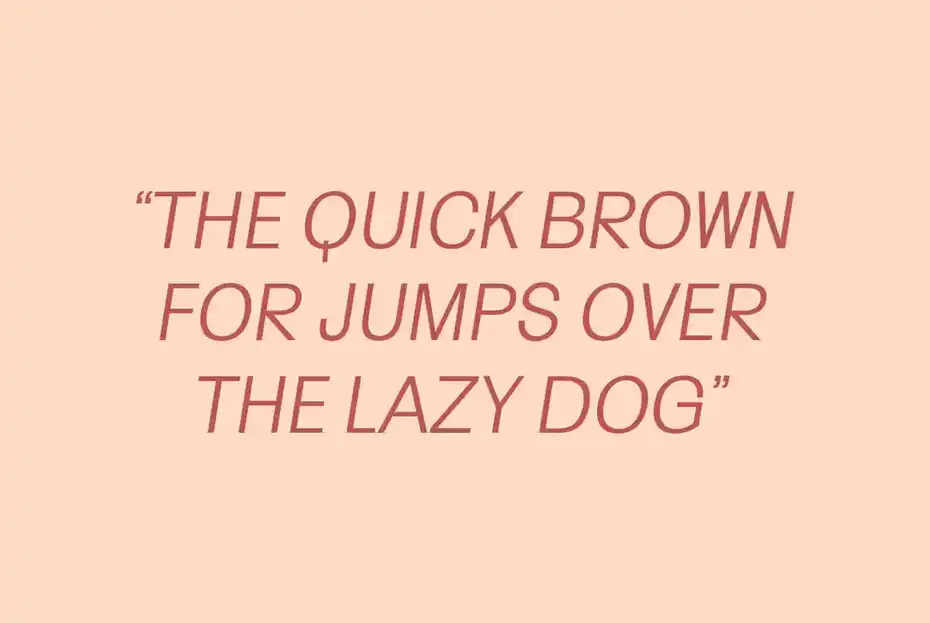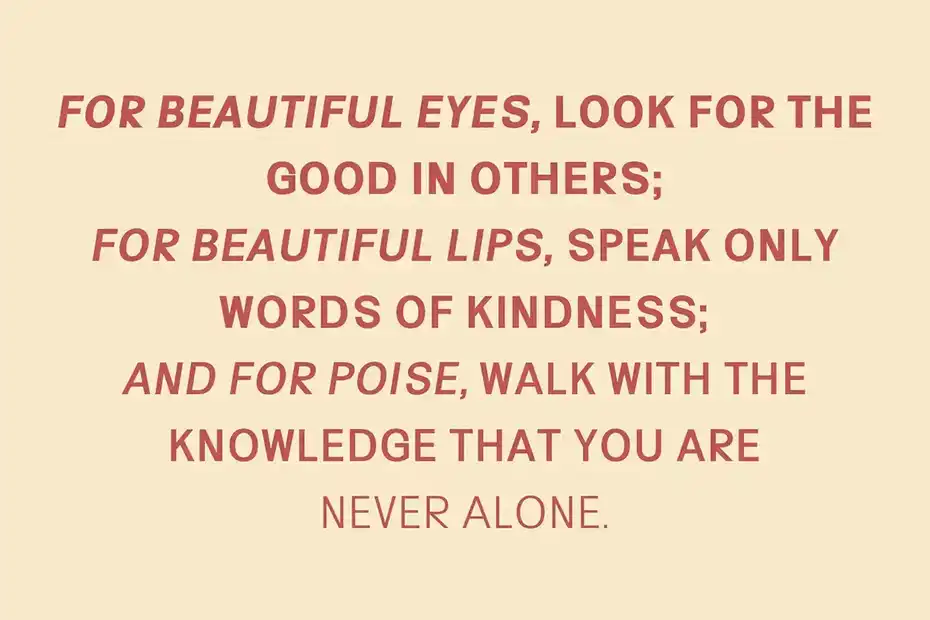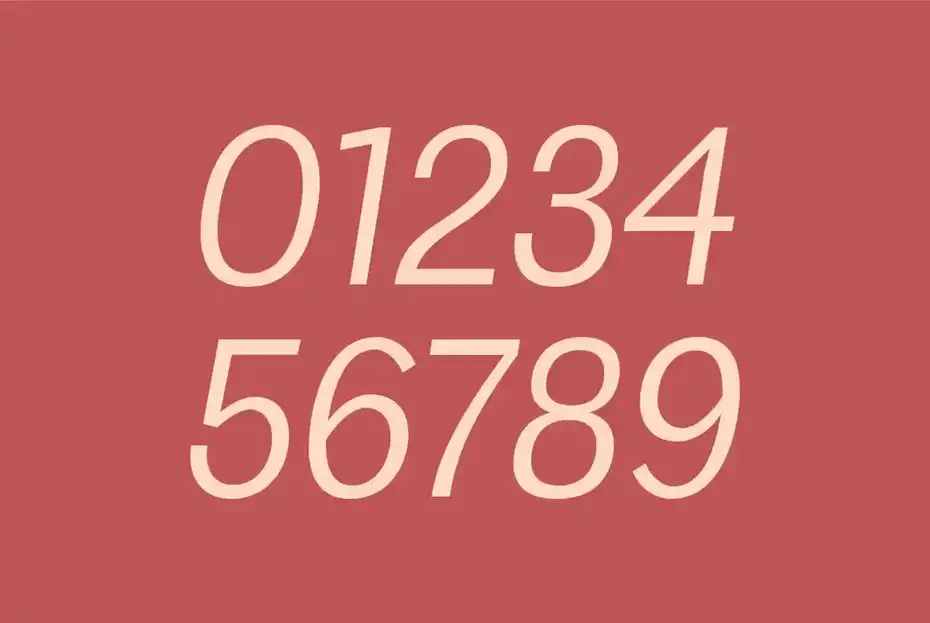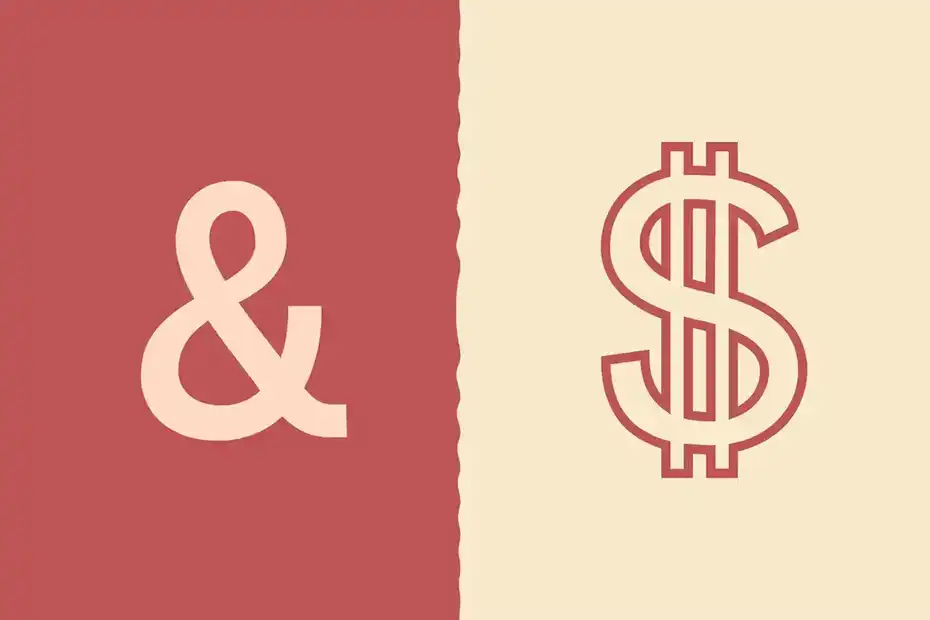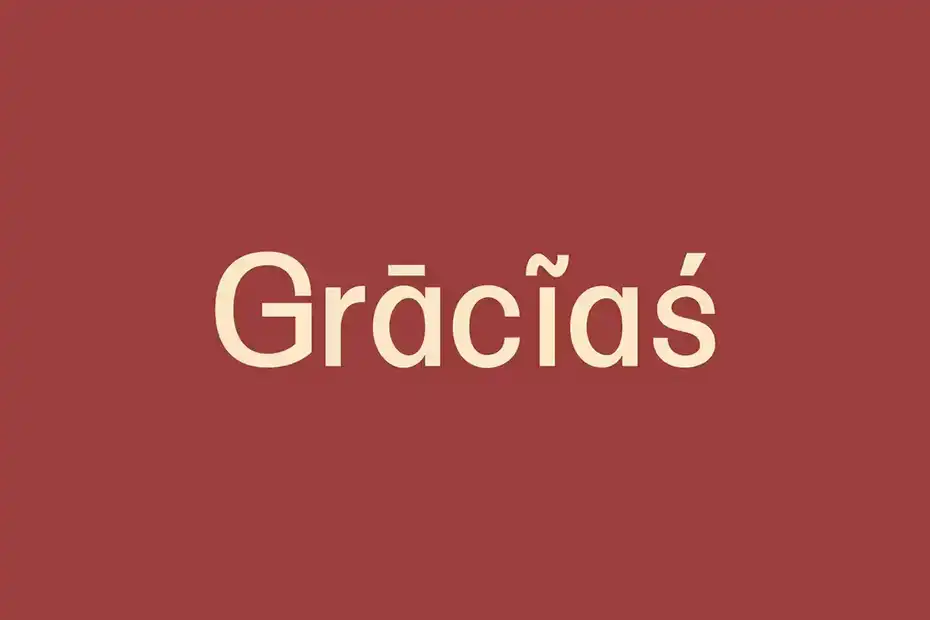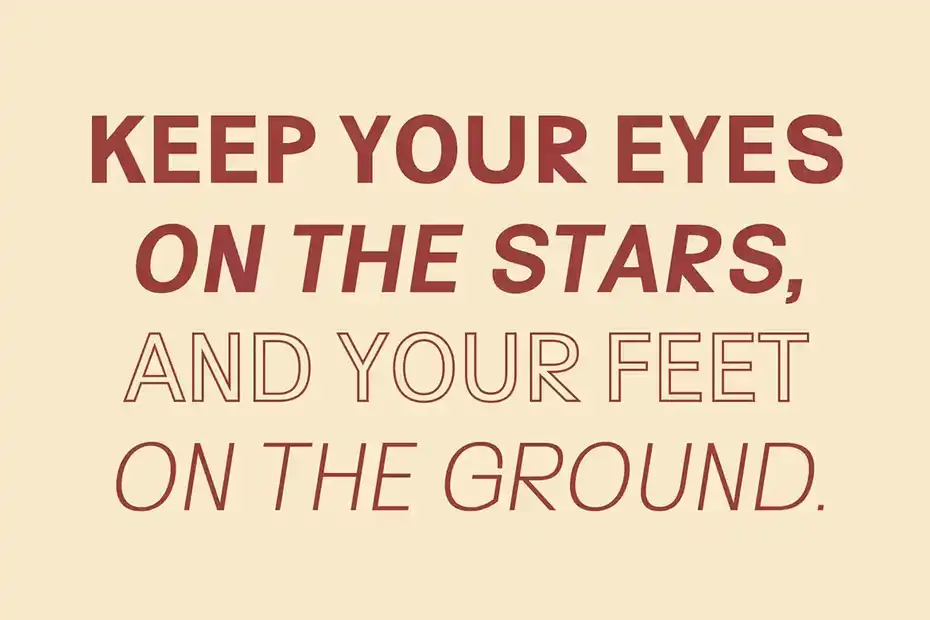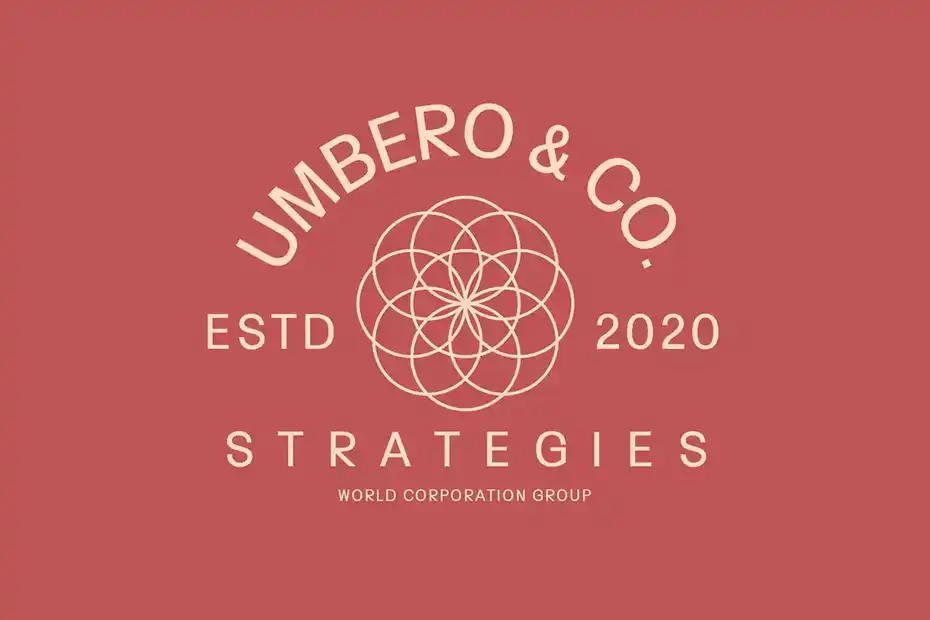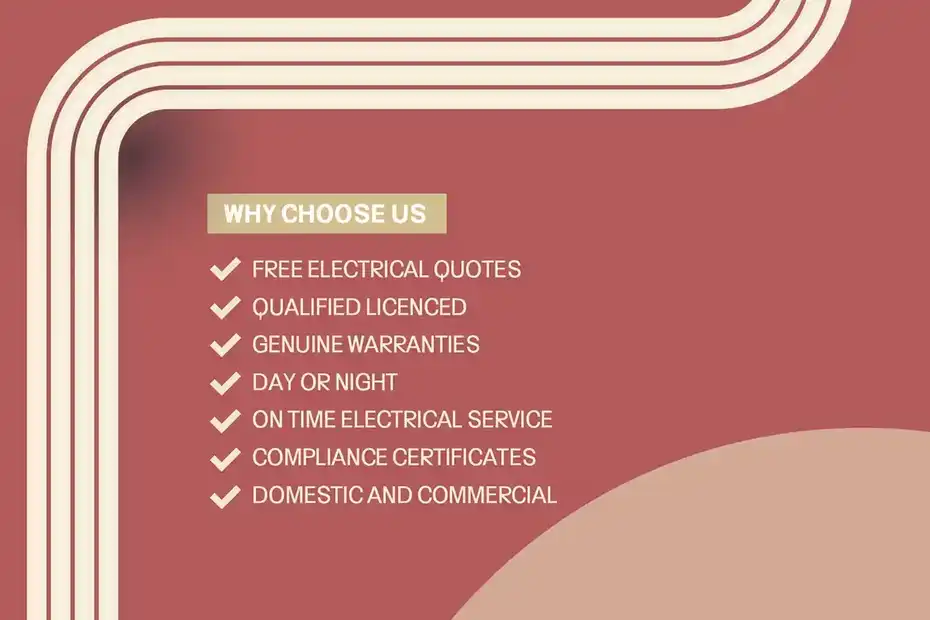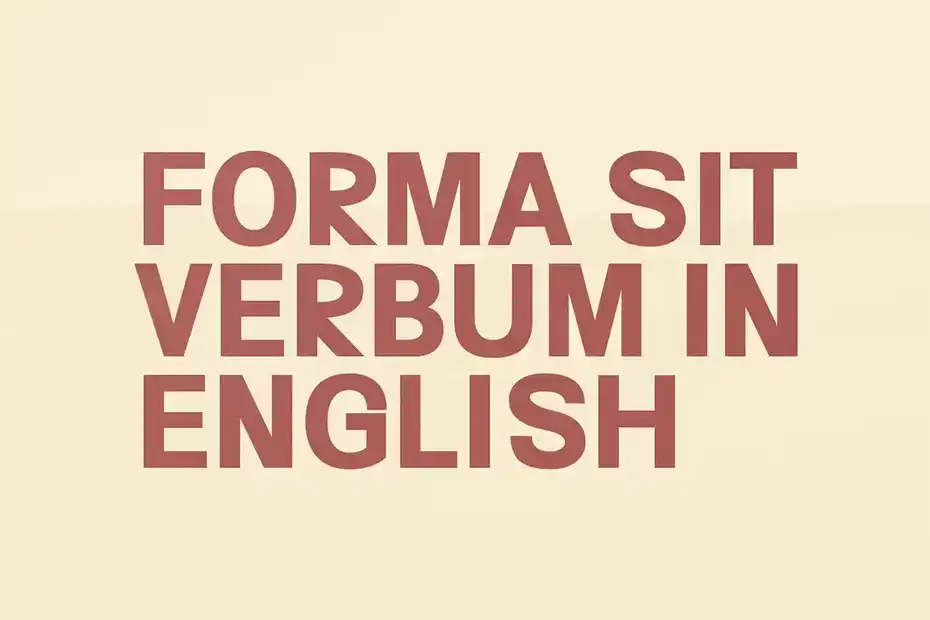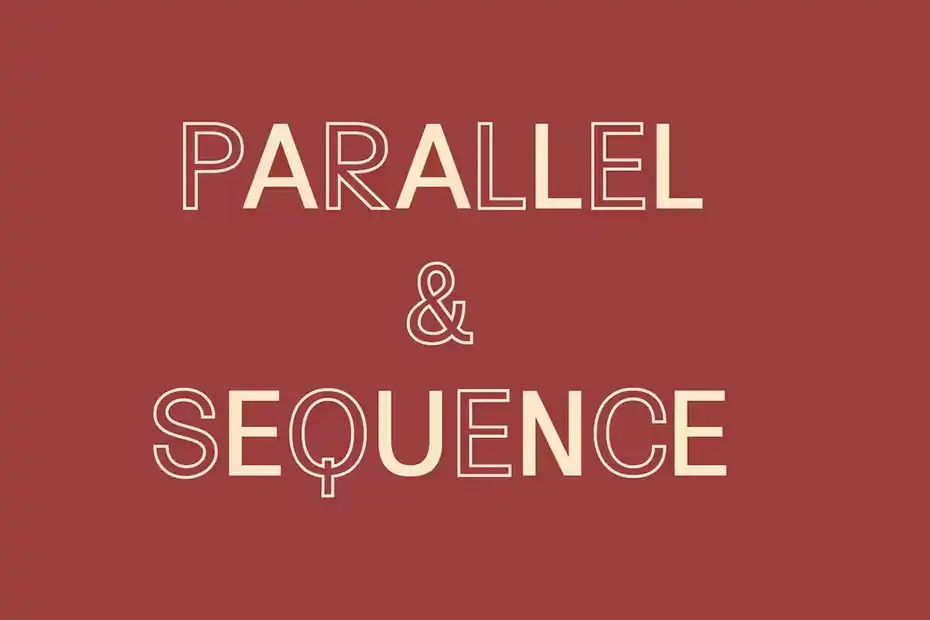
دانلود فونت انگلیسی ساده Hacim Simple Sans Serif Font Family
فونت انگلیسی ساده Hacim Simple Sans Serif Font Family : این مجموعه شامل یک فونت انگلیسی ساده است که برای لوگو، برندینگ، بسته بندی، کارت تبریک، پرزنتیشن، سرفصل، پوستر، نقل قول، عنوان، تیتر مجلات، طرح بندی وب، تایپوگرافی، تبلیغات، دعوت نامه،عنوان کتاب و غیره مناسب میباشد.
• عنوان مجموعه: Hacim Simple Sans Serif Font Family